文字の中が小さい丸形で切り抜かれているのですが、まるで本当にチーズのようにも見えるので、面白いフォントです◎
廻募
廻募(エモ)は、考古学文字のような、超巨大迷路を俯瞰したような、文字の中に何重もの線が入っているようなデザインが特徴的なフォントです。
瞬きノ明朝
瞬きノ明朝フォントは、文字がギザギザに揺れているようなユニークな加工が施されているインパクトあり、爽やかさを感じるデザイン明朝体フォントです。
ボトムズ
ボトムズフォントは、源ノ明朝をベースとして、沼の底のようなテクスチャを加えて制作されたデザインフォントです。
おそろしげ明朝
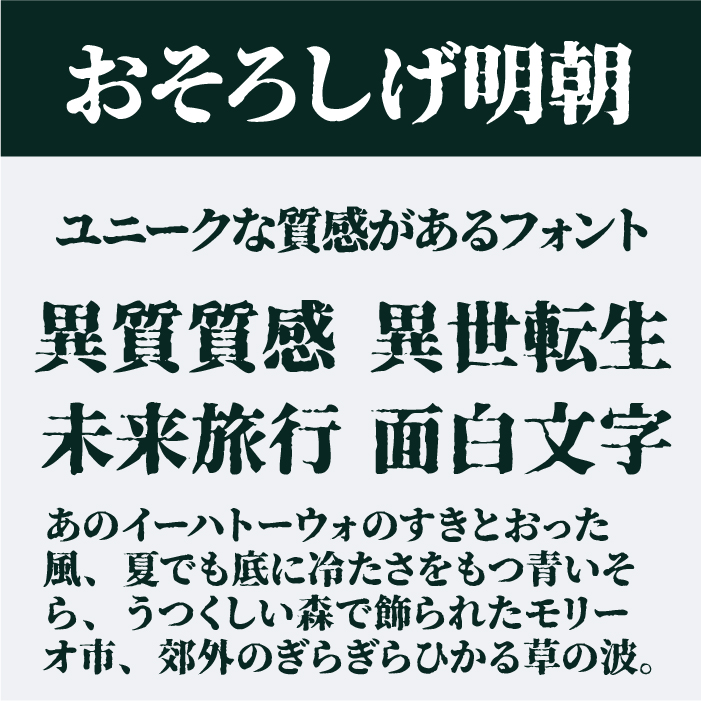
おそろしげ明朝フォントは、Noto Serifをベースとして、擦れと揺らぎが生む不穏な空気感が印象的な、ホラーテイストの明朝体です。